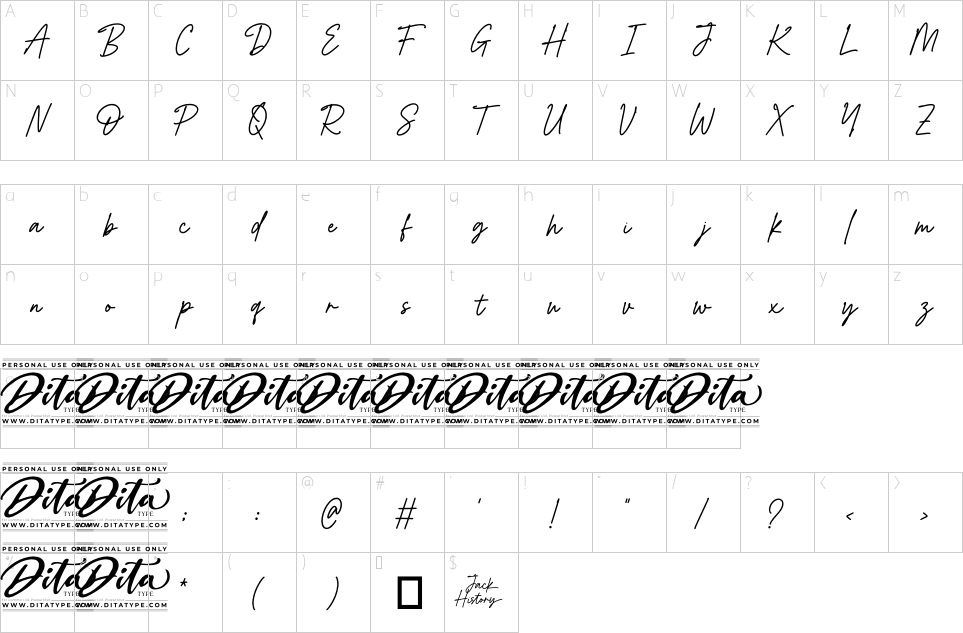
A fonte Jack History oferece um enriquecido conjunto de letras que se torna particularmente útil para qualquer projeto que exige um estilo histórico e elegante. Desenvolvida pela Dita Type, Jack History é uma fonte que carrega um encanto nostálgico, capaz de transmitir um sabor do passado ao seu design. Este é um bom exemplo de uma fonte histórica, adequada para aplicações que valorizam tanto a simplicidade quanto a elegância, seja para design de logotipo, gráficos de página web ou até mesmo para artesanato manual. Com uma elegante presença, Jack History não apenas oferece uma aparência atraente, mas também oferece uma versatilidade que permite que você personalize o seu design de acordo com suas necessidades. Com um download de 1.175 vezes, Jack History é uma fonte que está ganhando cada vez mais popularidade entre os designers que procuram uma fonte histórica para seus trabalhos.